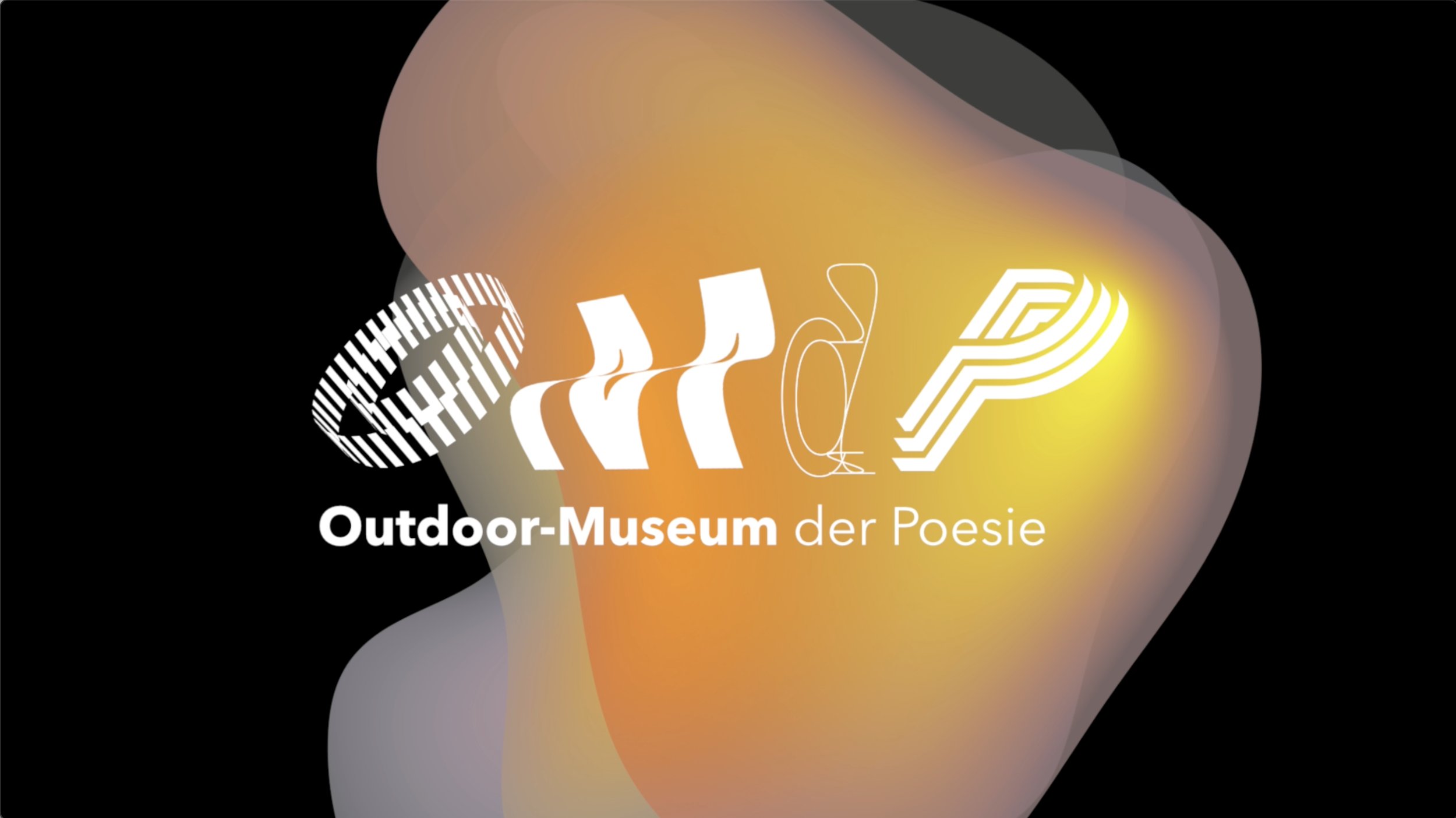
Logo für das Outdoor-Museum der Poesie
Das neue Logo des »Outdoor-Museums der Poesie« zieren vier von HfG-Absolvent Franz Weid entwickelte »Glyphen. Sie sind Weids Alphabet »Dimensional Fonts« entnommen, das durch ein eigens geschriebenes Skript digital erzeugt wurde.
»Die Bildhaftigkeit von Weids Glyphen entspricht dem Geist des Outdoor Museums der Poesie und der Grundidee der Stiftung Schrift und Bild« erläutert HfG-Alumnus Jörg Schmitz. Er ist Initiator und Projektleiter des Outdoor-Museums der Poesie und Kurator der Stiftung Schrift und Bild.